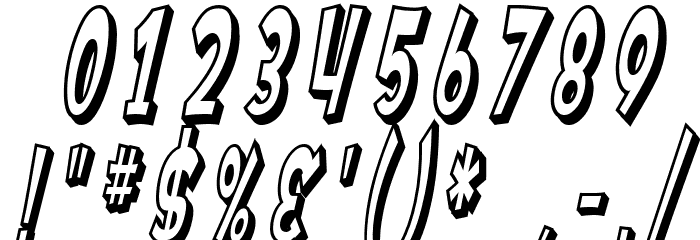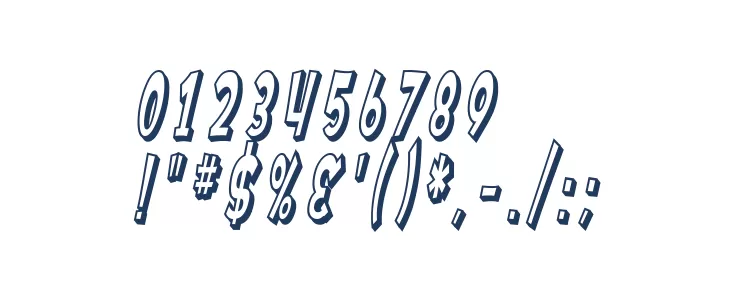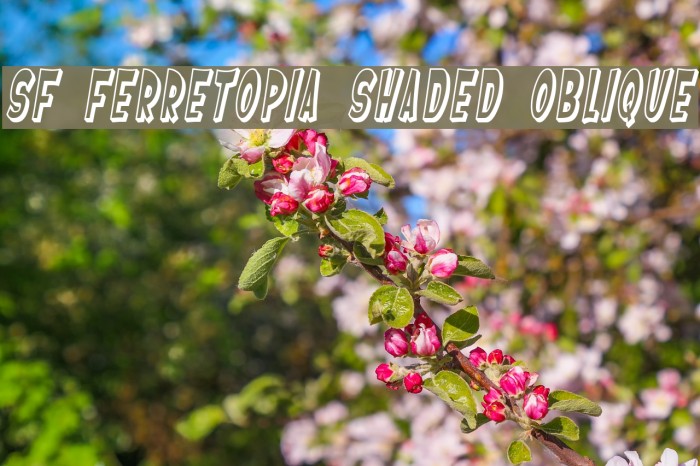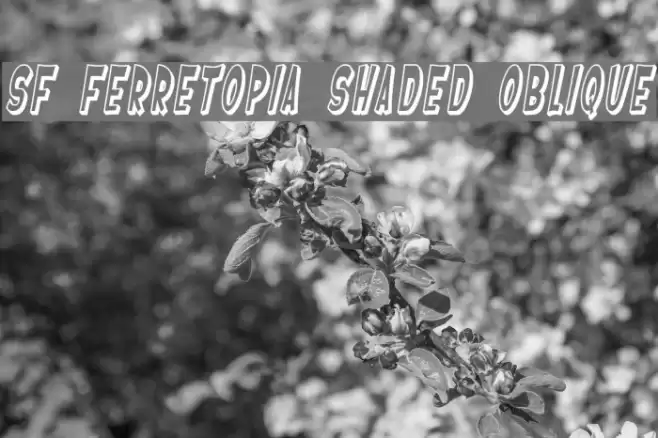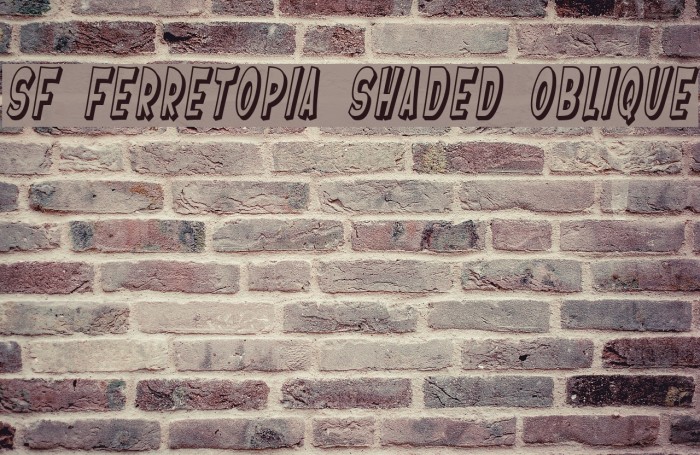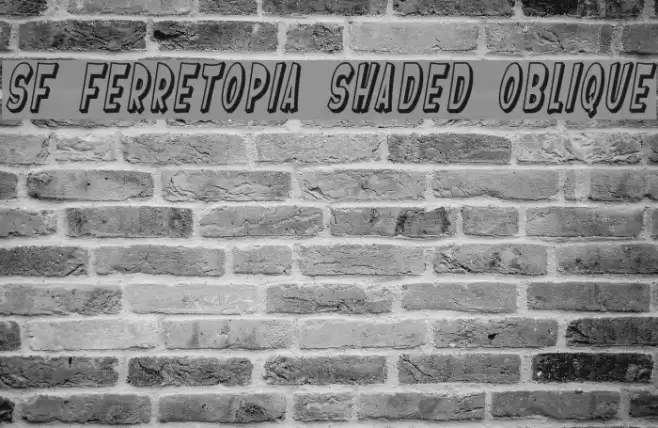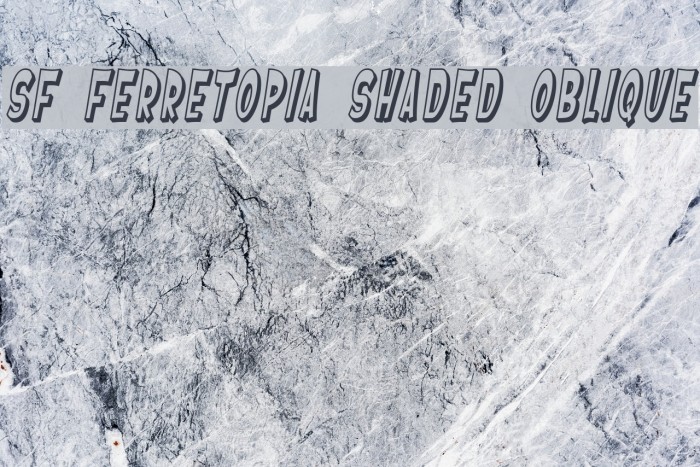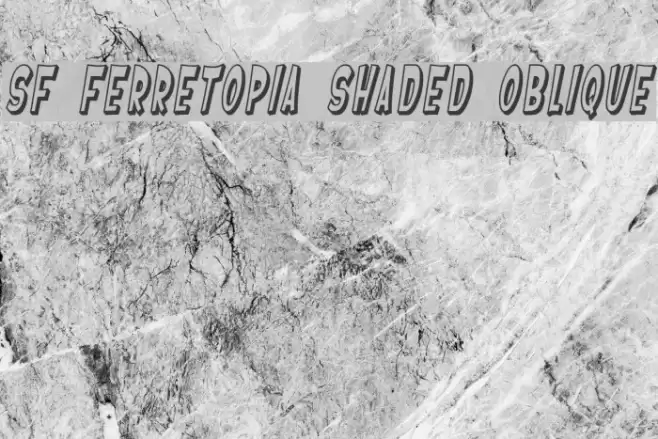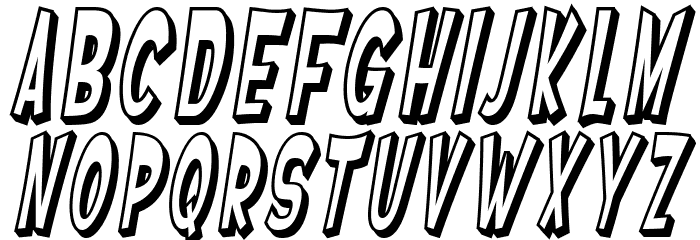
SF Ferretopia Shaded Oblique Font
✎ Comic
| Catégories | Comic |
| Style général | Playful, Dynamic |
| Projets proposés | Perfect for comic books, children's book covers, playful branding, and eye-catching posters. |